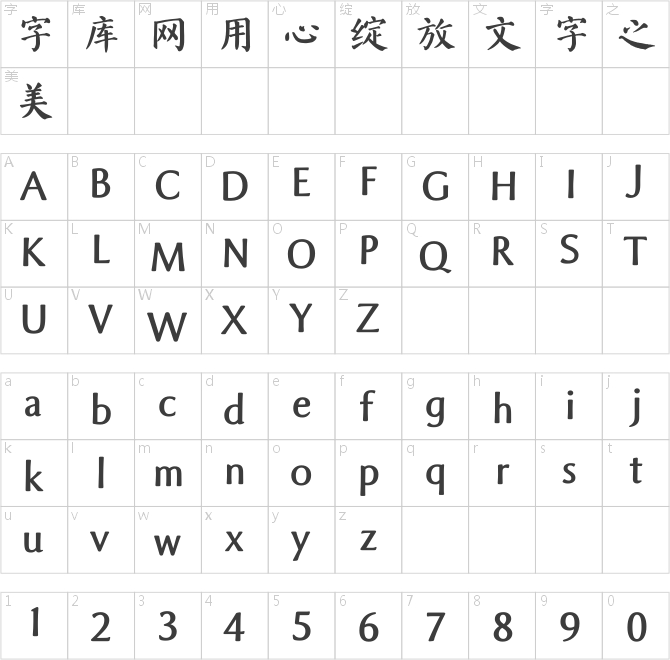
方正顏真卿楷書 詳情頁
字體名稱: 方正顏真卿楷書
方正顏真卿楷書
方正顏真卿楷書介紹
方正顏真卿楷書字體FZYanZQKSJF字庫是一款讓人賞心悅目、百看不厭的中文字體,適合各類廣告和產(chǎn)品包裝設(shè)計應(yīng)用,字體大小12.79MB,格式為TTF字體,上傳用戶是洛洛,作者/版權(quán)方為方正字庫